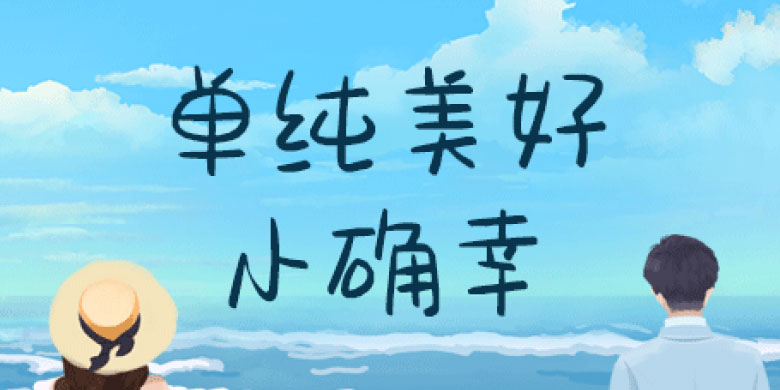
方正手迹-单纯美好小确幸
字体品牌: 方正手迹 设计师:刘晔 字体分类:创意书写 字体属性:精品字 字符集:简繁扩展(GBK) 发布时间: 2019
单纯美好小确幸这款字是一款个性的手写体,字体本身笔画简洁,给人透气的感觉,另外添加了少量的连笔,让字体有趣儿的同时又有种书写感。整体活泼生动,适用于文艺类儿童类的书刊、品牌广告和产品包装设计,以及社交网络的个性化用字。